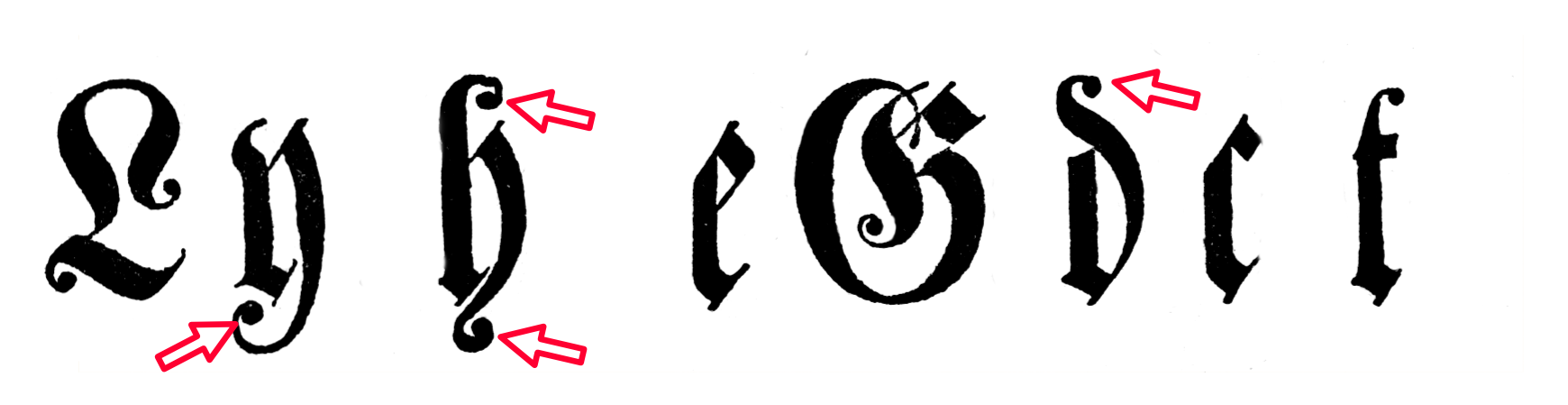
schmale Frakturschrift
ich suche eine "möglicht ähnliche" Schrift wie folgt (Anhang)test24.png
hierbei sollten die mit Pfeilen gekennzeichneten Schnörkel, Kringel, Zierschlaufen besondere Beachtung finden.
Die Chursächsische Fraktur kommt der Sache zwar nahe, aber eben nur etwas. Ebenso knapp vorbei die Luthersche Halbfett.
Die Coelnische Current Fraktur wiederum ist jedoch zu verspielt.
Der Ursprung ist Buch aus dem 18. Jh.